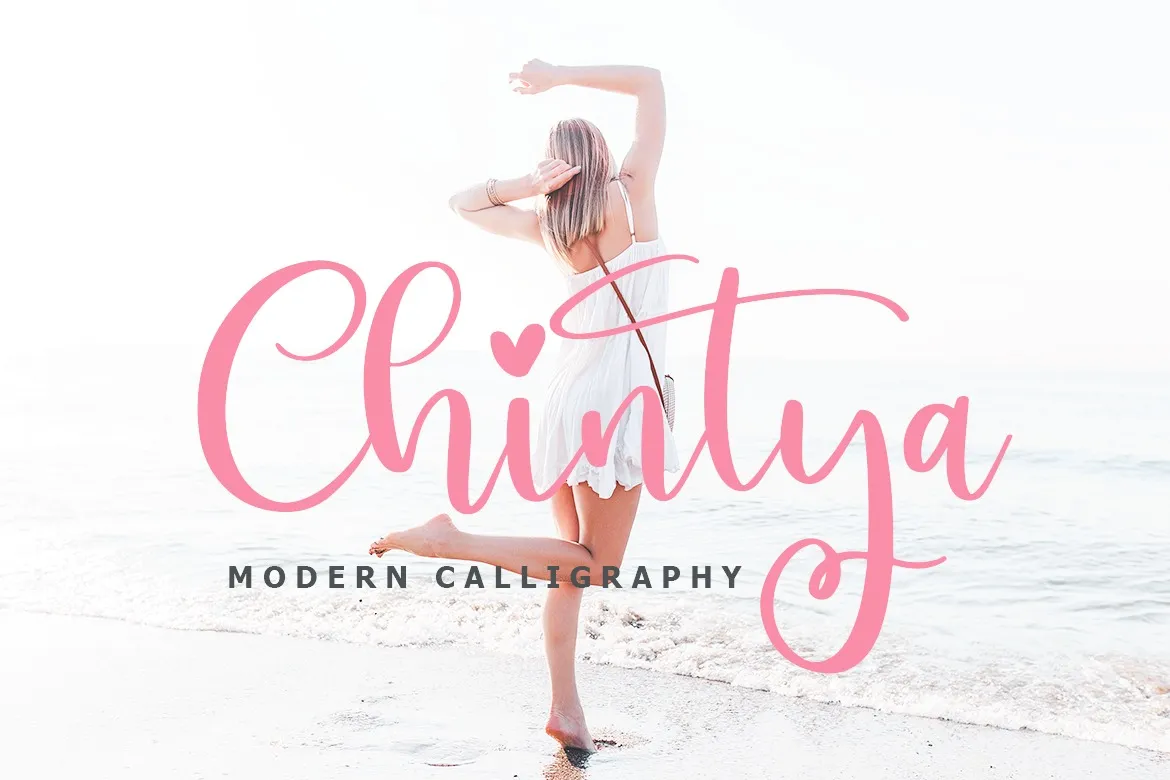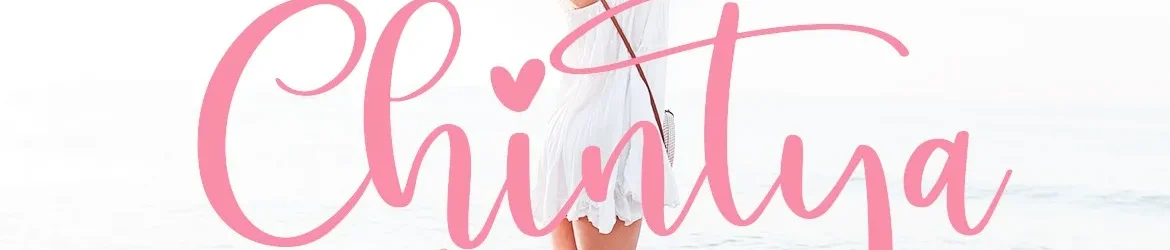
Chintya Font – Download Grátis
A fonte Chintya Font é uma nova escolha para quem busca a perfeição na combinação entre a simplicidade moderna e a elegância do estilo calligráfico feminino. Criada pelo designer lyanatha, esta fonte tem um desenho irregular sobre o qual os caracteres se baseiam, criando uma sensação única que se torna especialmente apreciável para uso em cartões de agradecimento, convites de casamento e até mesmo na criação de logotipos. Seu design moderno e trendy faz com que Chintya seja perfeito para qualquer tipo de projeto gráfico que deseja dar um toque único e personalizado, como cartas de cumprimentos escritas à mão ou desenhos empresariais. Ideal tanto para aqueles que buscam uma opção versátil quanto para designers criativos sempre em busca da perfeição.